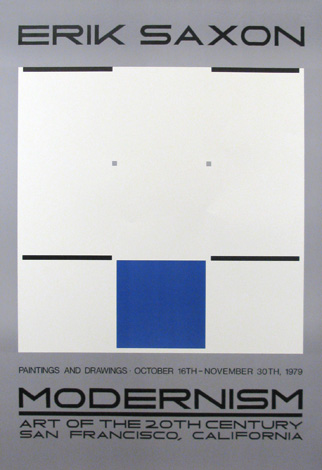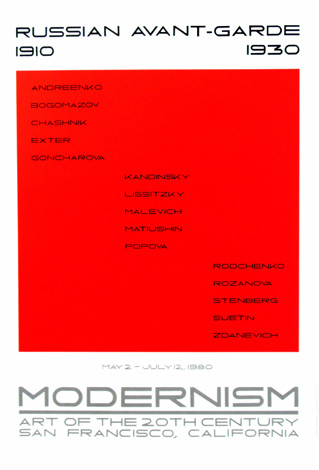
Suche Schriftart
ich bin auf der suche nach folgender Schrift:
Wo hast du denn das her? Vielleicht bringt uns das weiter …
ich bin auf der suche nach folgender Schrif ...[bildchen]...
Die Schrift ist einerseits sehr markant. Andererseits ist die Grafik zu niedrig aufgelöst damit http://new.myfonts.com/WhatTheFont/ etwas damit anfangen kann. Kannst Du eine höher aufgelöste Grafik auftreiben und WhatTheFont damit füttern?
Das SAXON sieht … wie soll ich nur sagen … naja. :cry: